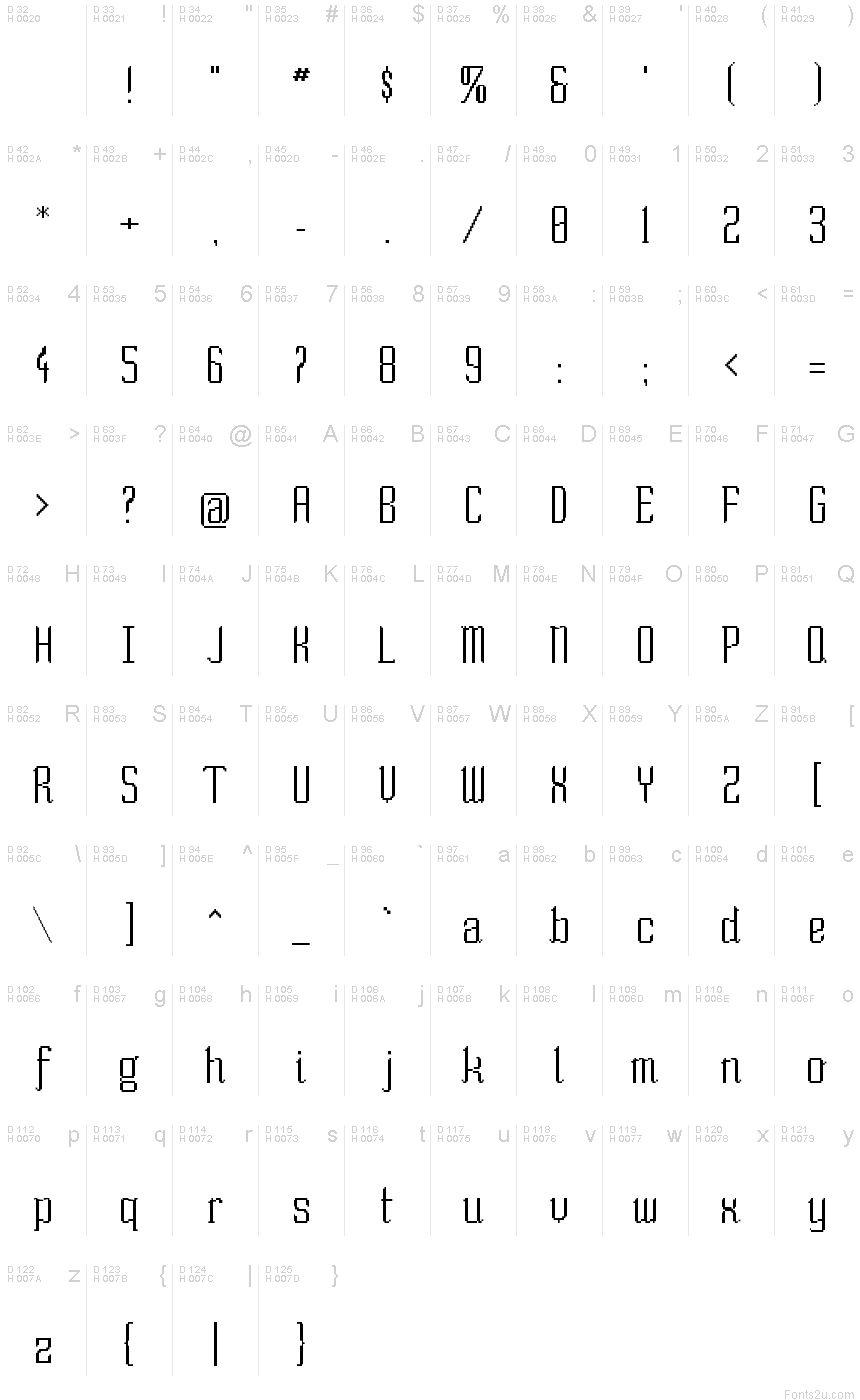
So Extended من Apostrophic Labs هو خط نقطي (Bitmap) مجاني بزوائد (Serif) يعكس جمالية الشاشات القديمة الصارمة. تمزج الحروف بين وحدات البكسل العريضة والخطوط الدقيقة غير المتوقعة، ليأتي التأثير العام وسطاً بين نصوص البرمجيات القديمة والعناوين الفيكتورية ذات التباين العالي.
هذا التباين يجعله خياراً قوياً لهوية ألعاب الريترو، وأغلفة المجلات المستقلة (Zines)، والملصقات، والرسومات المستوحاة من واجهات الاستخدام، والنصوص التحريرية القصيرة، حيث يمكن لهذا الخط المجاني استحضار الحنين الرقمي دون أن يبدو ليناً أو باهتاً. كما يعمل الخط بشكل ممتاز في الشعارات المدمجة وبطاقات العناوين، لأن الإيقاع الحاد للزوائد يمنح الكلمات، حتى القصيرة منها، طابعاً حازماً وصراماً.
خريطة محارف خط So Extended
خريطة محارف So Extended: ‏الأساسية لاتينية، الصفحة 1